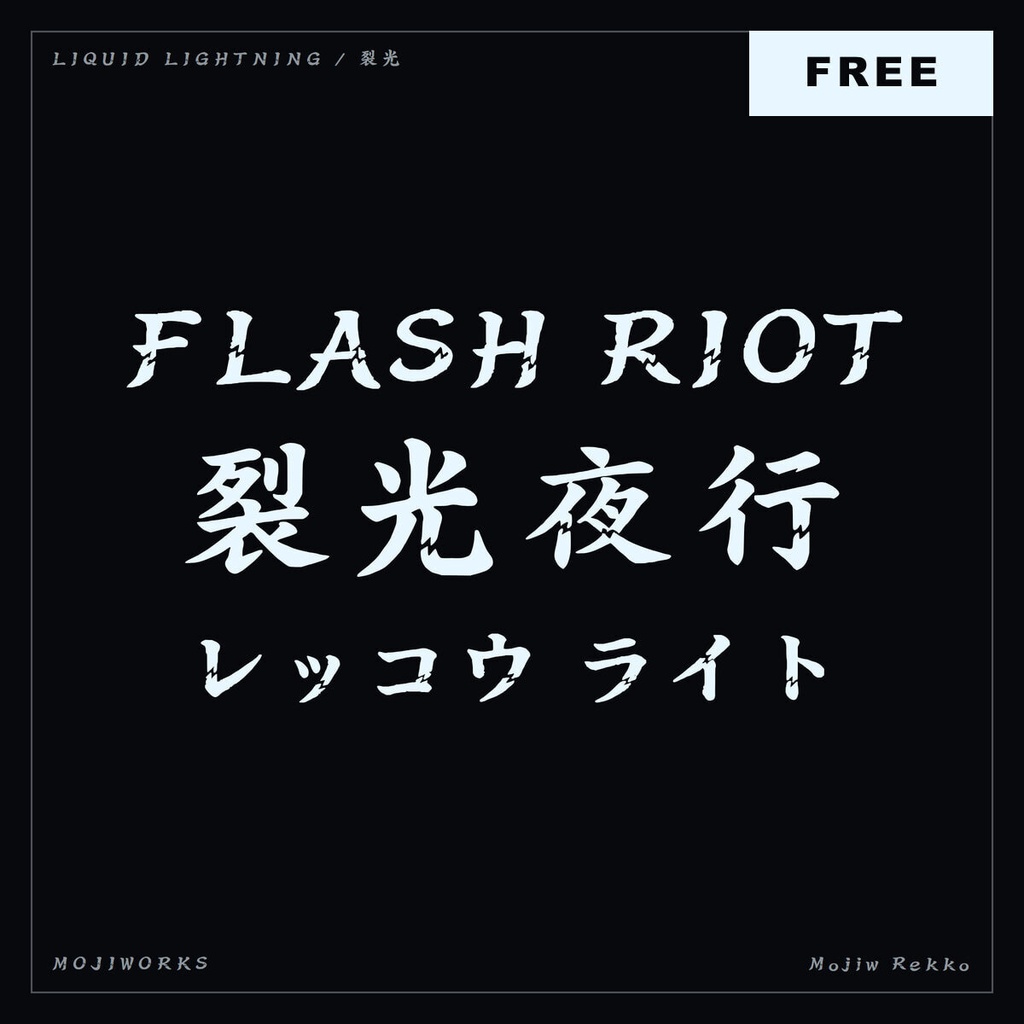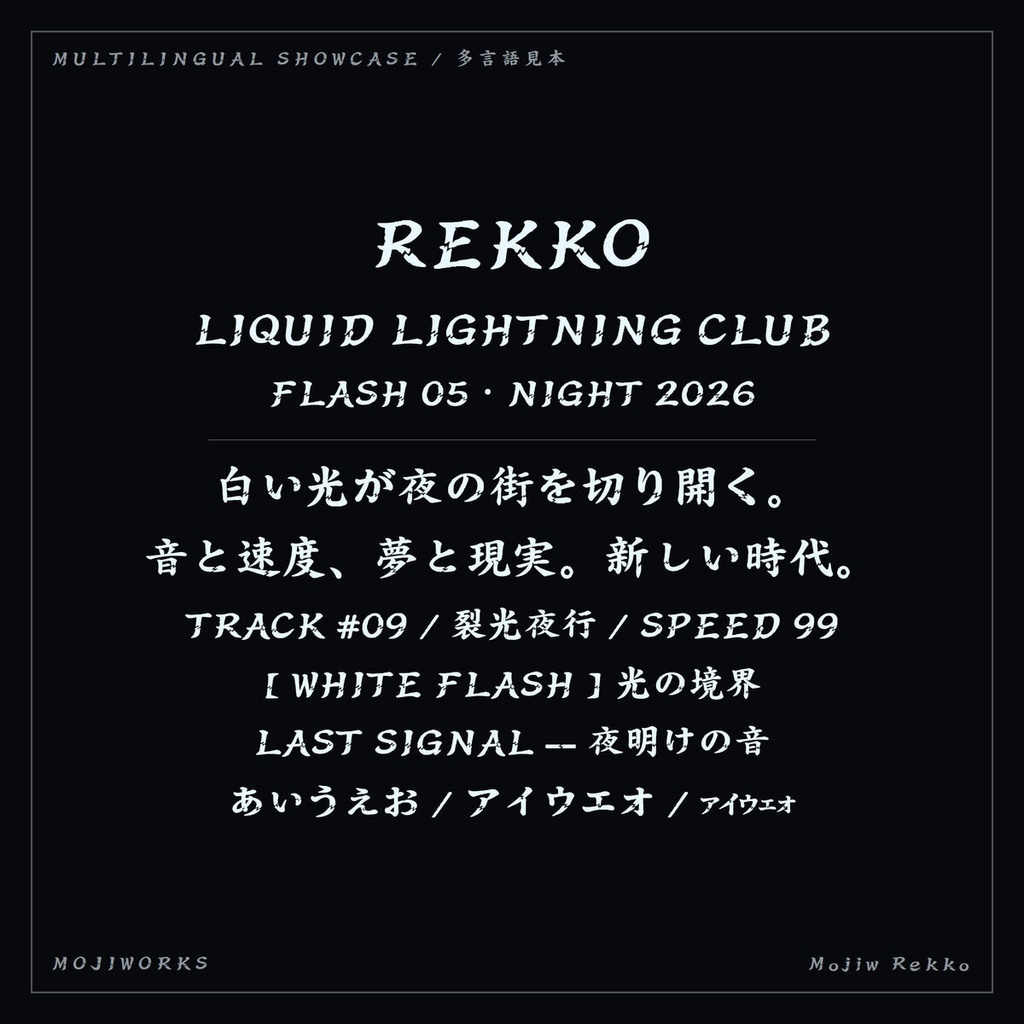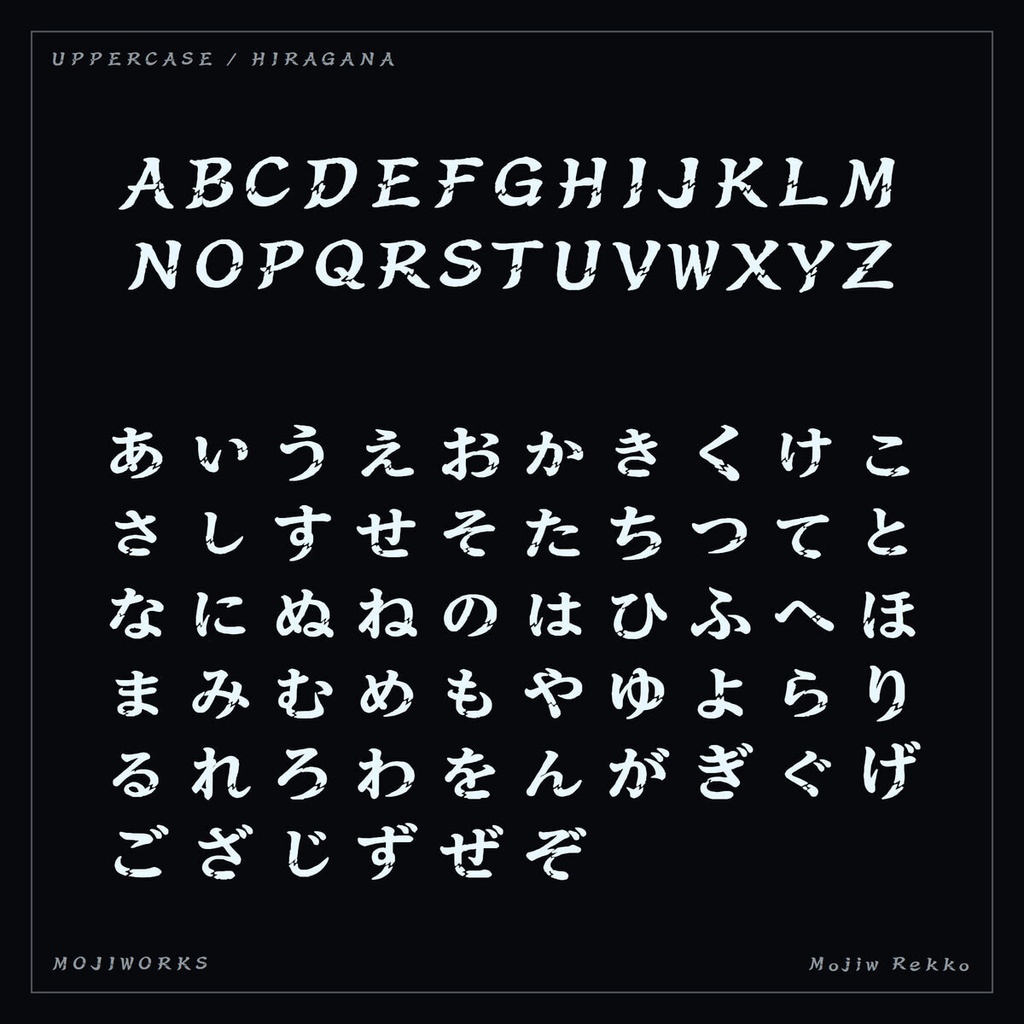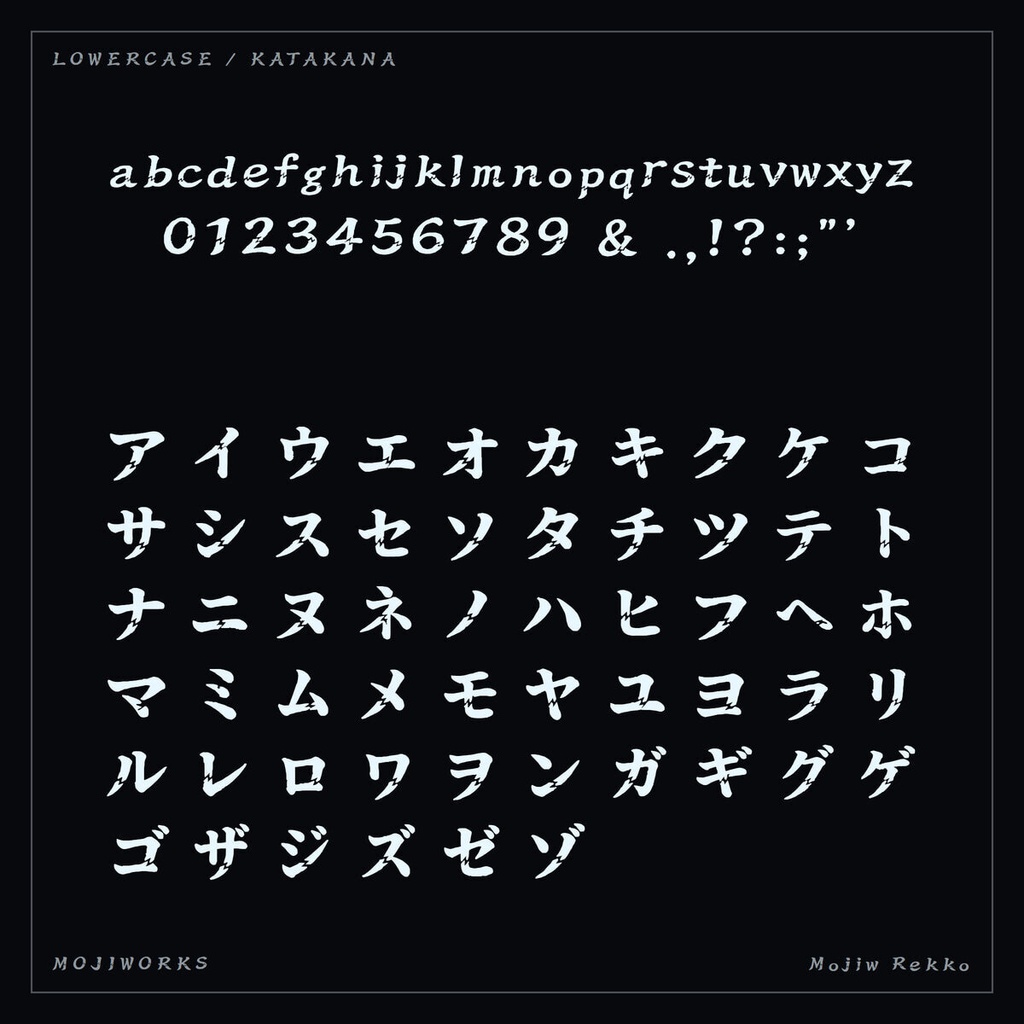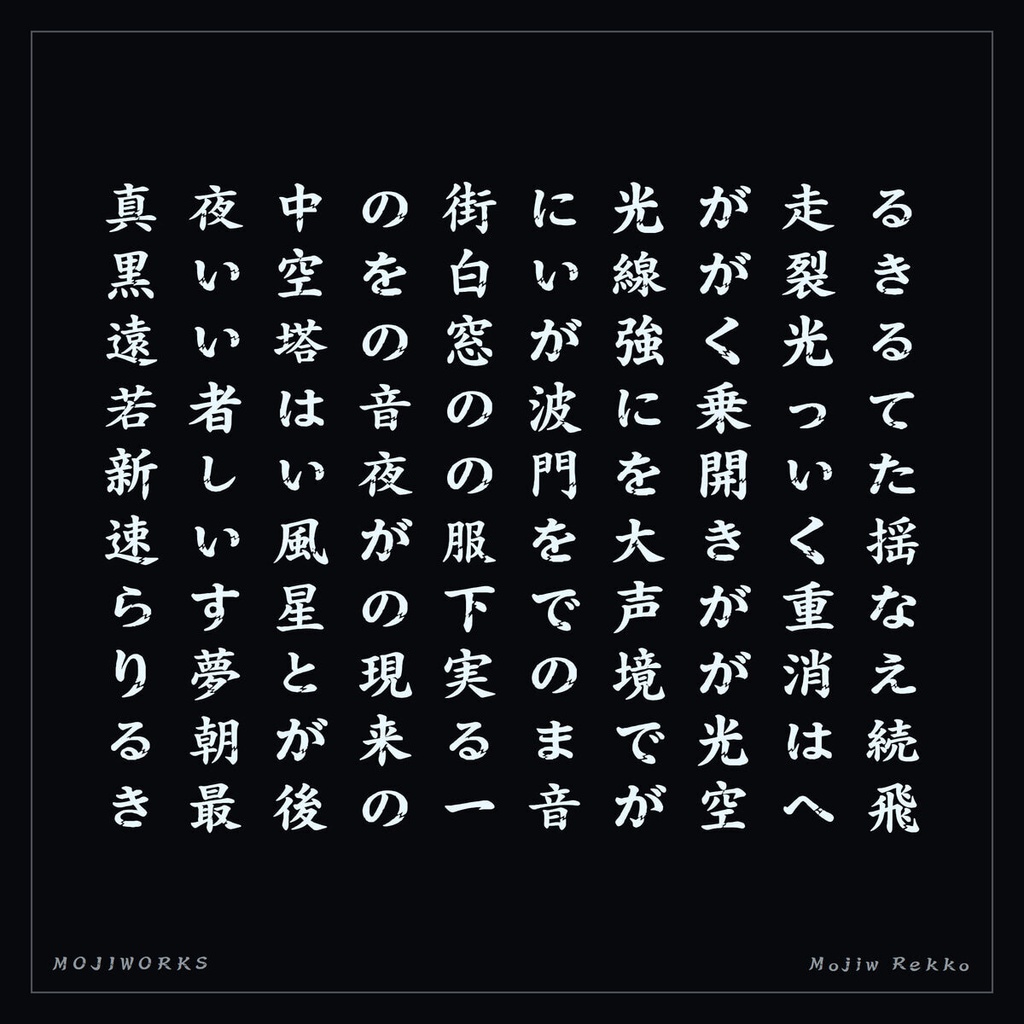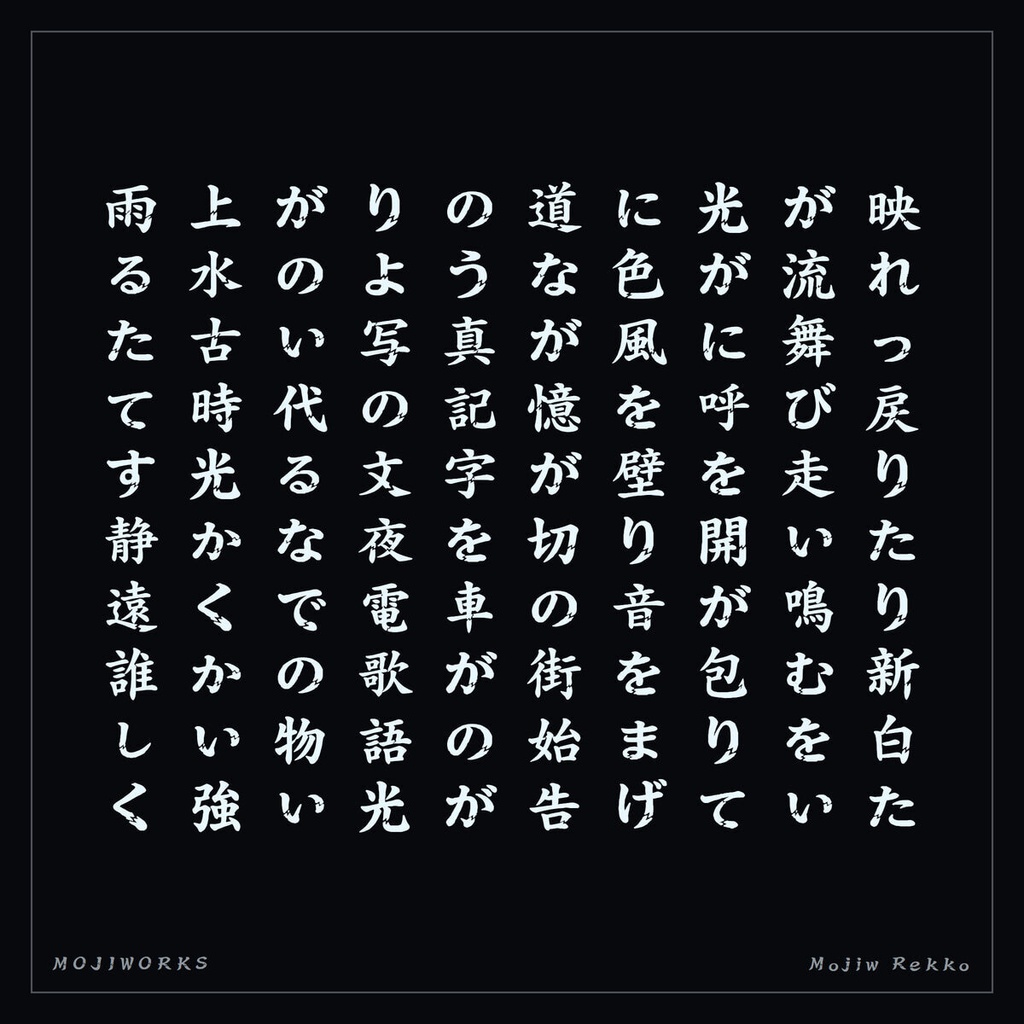
【無料・商用可】裂光 Rekko Free【フォント】|かな・英数字362文字
液体のような輪郭を白い稲妻が走る、Y2Kディスプレイ書体です。 A liquid Y2K display face split by bright lightning seams. 액체 같은 윤곽을 밝은 번개 이음새가 가르는 Y2K 디스플레이 서체입니다. 【用途 / Use / 용도】音楽ロゴ / ファッション / MV / ゲームタイトル / イベント For music logos, fashion, music videos, game titles, and events. 음악 로고 / 패션 / 뮤직비디오 / 게임 타이틀 / 이벤트 ━━━━━━━━━━━━━━━━━━━━━━━━━━━ 【無料版 / Free Edition / 무료판】 ━━━━━━━━━━━━━━━━━━━━━━━━━━━ ラテン文字・ひらがな・カタカナ・記号を収録した、商用利用可能な無料フォントです。 漢字は収録していません。ロゴ、タイトル、動画、配信、同人作品などでお使いいただけます。 This is a free, commercial-use font covering Latin, hiragana, katakana, and symbols. Kanji are not included. Use it for logos, titles, video, streaming, and indie works. 無料版 / Free edition: 362文字 — ¥0 ラテン大文字26 / ラテン小文字26 / 数字10 / ひらがな81 / カタカナ91 / 半角カナ・句読点61 / 記号・句読点66 / スペース1 ━━━━━━━━━━━━━━━━━━━━━━━━━━━ 【常用漢字フル版 / Full JA Upgrade】 ━━━━━━━━━━━━━━━━━━━━━━━━━━━ 無料版の全文字と常用漢字2,136字を収録した全2,498文字版は ¥3,200 です。 Full JA includes every free-edition character plus all 2,136 Joyo kanji (2,498 characters total). ▶ 常用漢字フル版 / Full JA: https://mojiworks.booth.pm/items/8657077 ━━━━━━━━━━━━━━━━━━━━━━━━━━━ 【フォント仕様 / Specification】 ━━━━━━━━━━━━━━━━━━━━━━━━━━━ 形式 / Format : OpenType TrueType (.ttf) / Web (.woff2) 文字コード / Encoding : Unicode 動作環境 / Platform : Windows / macOS / Web browsers 収録字一覧 / Charset : 各ZIP内の CHARSET.txt 同梱ファイル / Bundled files: .ttf — デスクトップ用 / desktop .woff2 — Web 用 / web README.txt / README.jp.txt LICENSE.txt / LICENSE.jp.txt CHARSET.txt — 収録字一覧 / character list portfolio.pdf — モジワークス全書体ポートフォリオ (EN) portfolio.jp.pdf — モジワークス全書体ポートフォリオ (JP) 商品プレビュー画像 / product preview images ━━━━━━━━━━━━━━━━━━━━━━━━━━━ 【利用規約 / License Summary】 ━━━━━━━━━━━━━━━━━━━━━━━━━━━ ご購入・ダウンロードにより本規約に同意したものとみなします。著作権は Mojiworks に帰属します。 By downloading or purchasing this font you agree to these terms. © Mojiworks. The bundled LICENSE.txt / LICENSE.jp.txt is authoritative; this is a summary. ●使用条件 / Permitted use - 1ライセンス = 購入者本人。個人・商用利用OK。 One license is granted to a single user (the purchaser). Personal and commercial use is permitted. - 静的・ラスタライズ済み成果物(印刷物 / 動画 / グッズ / ロゴ / タイトル / ラスタライズUI)は常に許可。 Static, pre-rendered output (print, video, merchandise, logos, titles, rasterized UI text) is always permitted. - 同梱 .woff2 を購入者本人のサイトで CSS @font-face によりWebフォントとして使用可。 The bundled .woff2 may be served via CSS @font-face on a website owned or operated by the purchaser. ●条件付き利用 / Conditional use — game / app / software embedding - ゲーム・アプリ・ソフトへの組み込みは、エンドユーザーが生の .ttf / .woff2 を抽出できない形式に限り許可。 例: SDF / MSDF フォントアトラス、ビルド時ビットマップ化、暗号化・独自フォーマットへのパッキング、難読化コンテナ等。 Embedding in games, apps, or software is permitted only if the raw .ttf / .woff2 cannot be extracted by end users (e.g. SDF/MSDF font atlases, build-time bitmap atlases, encrypted or custom asset packing, obfuscated containers). - 生の .ttf / .woff2 をビルドにそのまま同梱する用途は標準ライセンス対象外です。別途「ランタイム組み込みライセンス」をご相談ください。 Shipping the raw .ttf / .woff2 inside a build is NOT covered by the standard license — please contact us for a separate runtime-embedding license. ●利用規模 / Scale limit - 標準ライセンスは 1製品 / 1サイト あたり 年間およそ 100,000 インストール/ダウンロード/ユニークビジターまでをカバーします。 The standard license covers usage up to approximately 100,000 installs, downloads, or unique visitors per year, per product or site. - これを超える規模、または従業員 50 名超の組織(タイトルのパブリッシャー含む)でのご利用は「拡張ライセンス」をご相談ください。 Beyond this scale, or for organizations with more than 50 employees (including the publisher of the title using the font), please contact us for an extended license. ●禁止事項 / Prohibited - フォントファイル本体の再配布・譲渡・販売・貸与・サブライセンス。 Redistribution, resale, lending, or sub-licensing of the font file itself. - 生 .ttf / .otf の公開Webサーバー / CDN / ファイル共有サービスへのアップロード。 Uploading the raw .ttf / .otf to public web servers, CDNs, or file-sharing services. - 他者運営サイトからの .woff2 のホットリンク。 Hot-linking the supplied .woff2 from a site not owned by the purchaser. - フォーマット変換(独自Webフォント化を含む)、グリフデータの抽出、派生・類似フォントの制作・配布。 Format conversion (including building your own webfont), glyph extraction, or creating / distributing derivative or look-alike fonts. - 生成AIの学習、または画像・テキスト生成のスタイル参照としての使用。 Use for training generative-AI models or as a style reference for AI generation. - 本フォント自体の主たる商標としての登録(フォントで作った制作物の商標化は可)。 Trademark registration of the font itself as a primary mark (trademark of works made with the font is allowed). - 公序良俗に反する用途(誹謗中傷・犯罪助長・差別等)。 Use violating public order or morals (defamation, incitement to crime, discrimination, etc.). 詳細は同梱の LICENSE.txt / LICENSE.jp.txt をご確認ください。 For the full license, see the bundled LICENSE.txt / LICENSE.jp.txt. ━━━━━━━━━━━━━━━━━━━━━━━━━━━ 【カスタムフォント制作 / Custom Font Service】 ━━━━━━━━━━━━━━━━━━━━━━━━━━━ あなたのプロジェクトの世界観・雰囲気に合わせた、完全オーダーメイドのフォント制作を承ります。 ゲーム / アニメ / ブランド / VTuber / 同人作品のロゴ・タイトル用書体、独自スタイルのディスプレイ書体、収録字の拡張など、お気軽にご相談ください。 We craft fully custom fonts tailored to your project's visual identity and requirements. Please contact us for original display faces, logo/title fonts, expanded character coverage, extended licenses, or runtime-embedding licenses. ▶ Mojiworks ショップ / Shop: https://mojiworks.booth.pm/